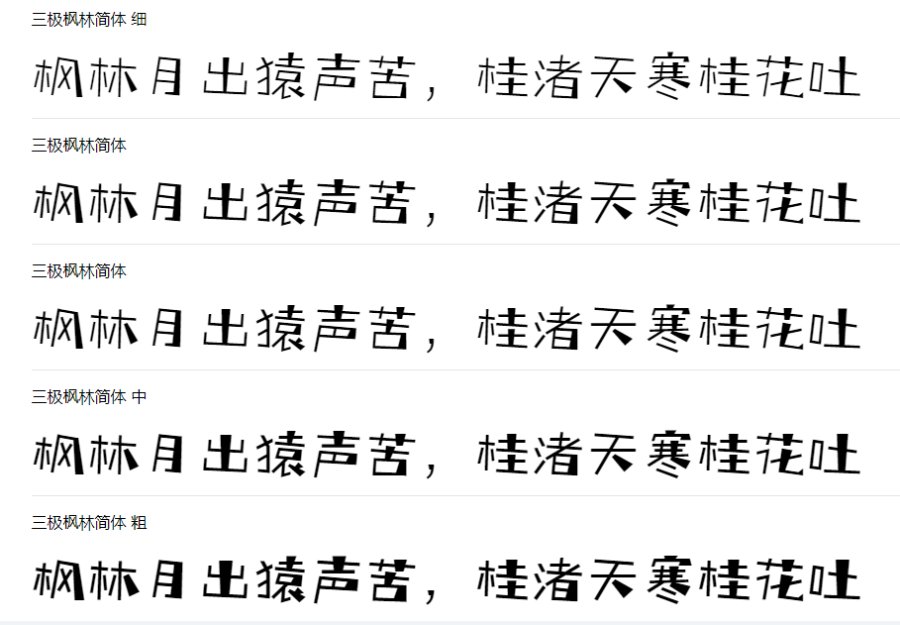
电商卖货专用商用字体有哪些?
给大家推荐黑体字,因为相对来说黑体字比较醒目,很快就能抓住消费者的吸引力。
三极枫林简体由三极字库出品,字体工整简洁,笔画设计为左细右粗,整体风格是向右边倾斜,字体风格飘逸随性,视觉效果抢眼,个性突出,具有强烈的视觉冲击力。该字体有5个不同的字重,可根据使用场景不同选择相应的字重。
三极枫林简体